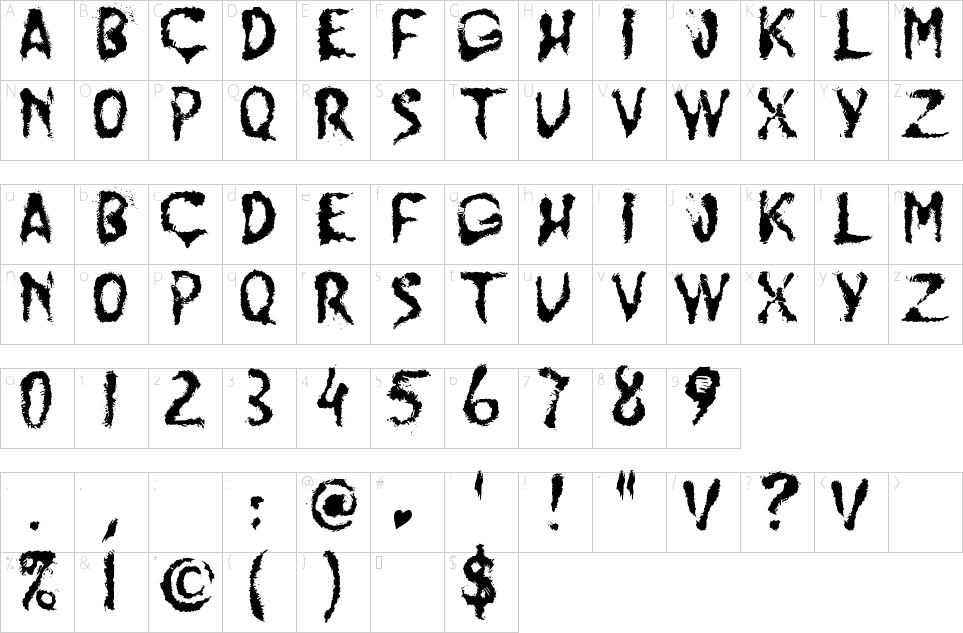
A Jump Burn IP font é uma opção grata para designers que procuram uma fonte moderna e dinâmica. Desenhada pelo criador Poemhaiku, essa fonte é perfeita para projetos digitais de nível médio a avançado, combinando facilmente com outros estilos de fonte para criar um design visual único. Esta fonte tem sido baixada cerca de 3.905 vezes, demonstrando seu valor e popularidade. Suas linhas curvas e detalhes leves criam um efeito visual chamativo, tornando-se uma escolha popular para texturas digitais, logotipos, e até mesmo para gráficos e design gráfico. Se procura uma fonte moderna e fácil de usar, a Jump Burn IP é um excelente investimento.